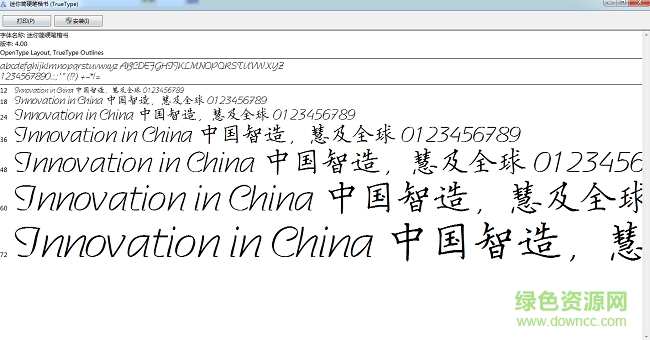
jyinbikai免費(fèi)版
Jyinbikai字體又叫迷你簡(jiǎn)硬筆楷書字體,字形清秀挺拔,結(jié)構(gòu)精妙,線條生動(dòng)優(yōu)美,極具欣賞價(jià)值,適用于印刷打印、海報(bào)設(shè)計(jì)、平面設(shè)計(jì)等領(lǐng)域,需要這款字體的小伙伴快來(lái)下載吧!
jyinbikai